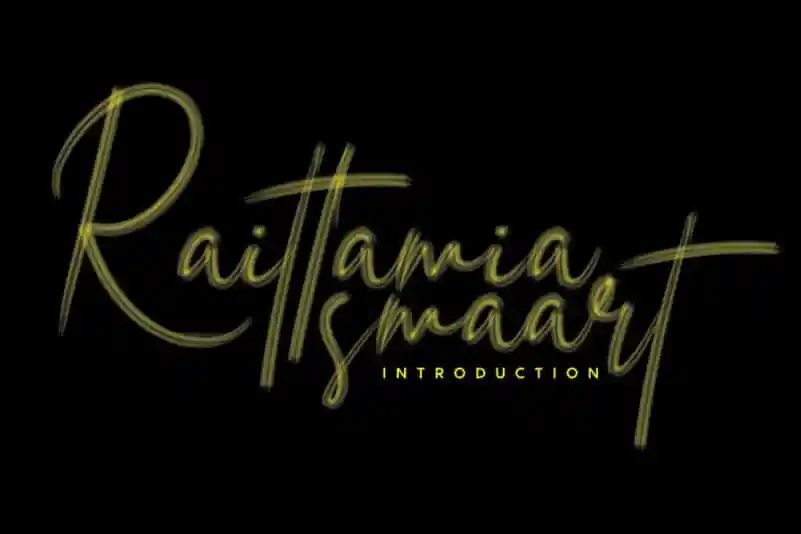
Raittamia Brush Font – Download Grátis
Descubra a encantadora Raittamia Brush Font, uma elegante caligrafia feita especialmente para quem valoriza o amor pelos detalhes e busca estilo único. Inspirada na perfeição de um belo caderno de registro ou no instante em que duas pessoas decidem se entregar completamente ao amor. Com sua escrita fluida e lisa, ela é uma fonte ótima para criar cartões de casamento incrivelmente bonitos, arte de assinatura encantadora, postagens sociais visíveis e tudo mais entre as mãos dos criativos. Adquira a Raittamia Brush Font hoje e deixe que seu design fale por si mesmo!